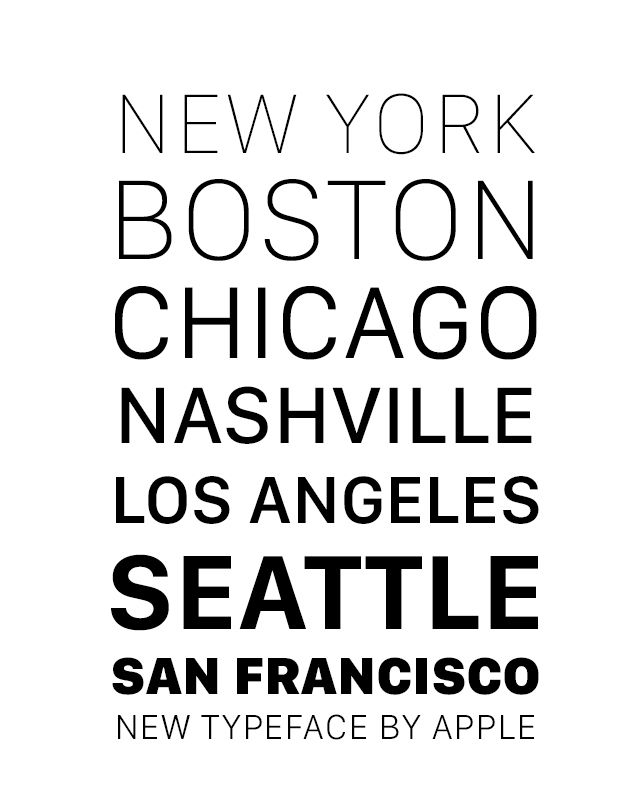
Дизайн для iOS: как выбрать размер шрифта (для iOS11)
Создаёте дизайн приложения для iPhone или iPad и не знаете, какие размеры шрифтов лучше использовать? Тогда ловите мой конспект, который я быстренько сварганил для тех, кто (а) пользуется San Francisco — шрифтом Apple по умолчанию (или чем-то похожим) и (б) хочет придерживаться стиля iOS.
Типографика для iPhone: гайдлайны
Здесь я кратко описал стили, ниже найдете наглядные примеры и более подробные рекомендации.
Давайте подробно разберём каждый из элементов, да с примерами. Поговорим не только про то, какой кегль где использовать, но и в целом о том, как Apple стилизует тексты.
Заголовок
В iOS 10 используются массивные заголовки, вроде слова «Inbox» на картинке ниже — кегль здесь 34pt, и это самый крупный текст, который можно встретить на iPhone.
А вот при прокрутке заголовок уменьшается до 17pt — размера по умолчанию для тех текстовых кнопок и ссылок.
Обратите внимание, что заголовок сжимается до размера текста по умолчанию, однако тут у него бòльшая жирность и располагается он сверху по центру — ясно, что это заголовок. Для начинающего дизайнера Эрика (меня, то бишь) это стало откровением, потому что я всегда думал, что заголовок обязательно должен быть крупнее, чем обычный текст (а не просто жирнее по начертанию).
Списки
Списки — основа мобильных приложений. Даже не задумываешься, какие элементы — на самом деле списки, пока не поместишь их на узкий вертикальный экран. Давайте посмотрим:
В режиме списка — например, в электронной почте — iOS подаёт имя отправителя как текст стандартного размера (17pt), а тему письма и предпросмотр — как второстепенный текст, меньший по размеру (15pt). На этом стоит заострить внимание — когда я делал свои первые шаги в дизайне, меня тянуло сделать обратное: для основного текста установить размер по умолчанию, а имя отправителя сделать ещё больше.
В разделе настроек сами пункты написаны текстом по умолчанию, хотя заголовки внутренних разделов (напр. «AirDrop») — мельче (ничосе!). Но несмотря на то что заголовок меньше, он толще по начертанию, то есть всё же воспринимается как заголовок.
У подписей («AirDrop lets you share instantly…») размер 13pt, самый маленький среди всех наших интерфейсных примеров.
Элементы управления
Давайте-ка взглянем на некоторые элементы управления.
Сейчас всё должно казаться уже достаточно понятным. Единственное, что может вызвать удивление — это сегментированная кнопка, текст на которой размером 13pt (кажется, что маловато). Я так подозреваю, Apple посчитал, что раз уж какие-то из этих кнопок будут выполнять несколько функций, то шрифт на них по умолчанию должен быть более мелким, даже если функции всего две.
Параметры текста в поисковой строке — значения размера и жирности — стоят по умолчанию, а вот цвет текста бледный, и меняется, когда начинаешь вводить запрос.
Модальные окна
Этот небольшой попап отлично иллюстрирует то, как в Apple оформляют тексты.
Размер заголовка: по умолчанию. Он может показаться недостаточно крупным, но мы о таком уже говорили выше. Жирное начертание компенсирует небольшой размер.
Размер пояснительного текста: 13 pt. Я предполагал, что он будет 15 pt, как и размер основного текста в электронных письмах, но, может, они просто захотели уместить тут текст в одну строку?
Размер текста при вводе пароля: 13 pt. Это было бы слишком мелко для ввода стандартного текста, но — как я подозреваю — здесь вы всё равно увидите только ряд чёрных точек, потому не столь важно, какого они размера.
Размер текста для слов «OK» и «Cancel»: по умолчанию, однако так как все надеются, что вы нажмёте на «OK», Apple чуточку больше обращает ваше внимание именно на это слово, дав ему более жирное начертание.
В размерах прослеживается четкая иерархия, тут можно почерпнуть несколько приёмов стилизации текста, но не обошлось и без странных несостыковок.![]()
Панель действий
И вот мы наконец добрались до панели действий (action bar), которая находится в нижней части экрана. Нигде больше в интерфейсе я не встречал настолько мелкого кегля — 10 pt. Я бы оставил такой мелкий шрифт на самый крайний случай.
Типографика для iPad: гайдлайны
На момент написания этой статьи (весна 2018) плотность пикселей у iPad была в целом ниже, чем у iPhone. Это значит, что элемент на iPad будет отображаться слегка больше, чем на макете или в приложении на iPhone. По этой причине большинство кеглей не разнится между айфонами и айпадами. Если вы работаете над дизайном для iPad-приложения, почитайте раздел про iPhone по тексту выше.
Как я говорил, самая большая разница здесь в заголовках. Пространства на экране айпада больше, и идеальный размер кеглей остаётся идеальным, однако в вашем распоряжении гораздо больше пространства (чем на айфонах) для того, чтобы сделать заголовки крупнее.